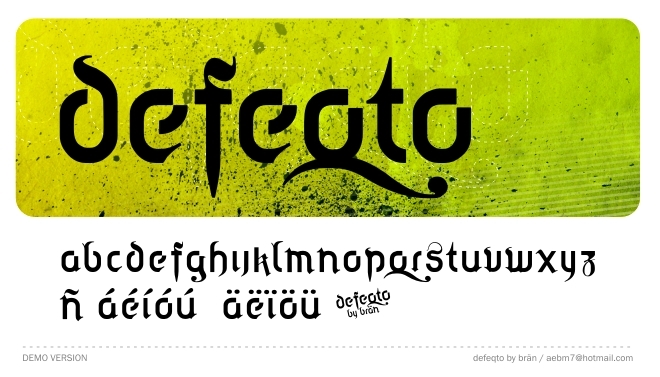
Defeqto, von Bran, ist eine kostenlose, moderne gotische Schrift mit einer eleganten Blackletter-Attitüde. Anstelle dichter mittelalterlicher Texturen besticht sie durch breite, fließende Kurven und markant gekappte Ecken; die langen, spitzen Unterlängen und der ausladende Schwung verleihen dem gesamten Design eine scharfe, theatralische Note.
Ideal für Poster-Überschriften, Musik-Branding, Buchcover, Titelschriftzüge und Logotypen, bei denen eine kostenlose Schrift sowohl gotische Stimmung als auch einen modernen, klaren Look vermitteln soll. Verwenden Sie sie für kurze Wörter, Mastheads, Monogramme oder Titelzeilen, die zeremoniell, aber nicht antik wirken sollen – denn diese Schrift bewahrt das Drama alter Skripte, ohne dabei überladen oder verspielt zu wirken.